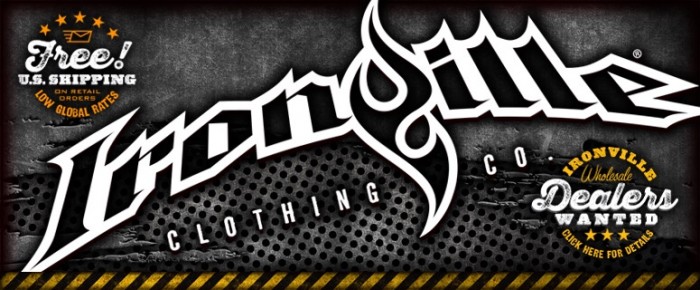
Blackletter-Style Font gesucht
Hat vielleicht jemand eine Idee welcher Font im angehängten Beispiel als Basis für das Wort "IronVille" gedient haben könnte? Kennt ihr eventuell ähnliche Fonts...?